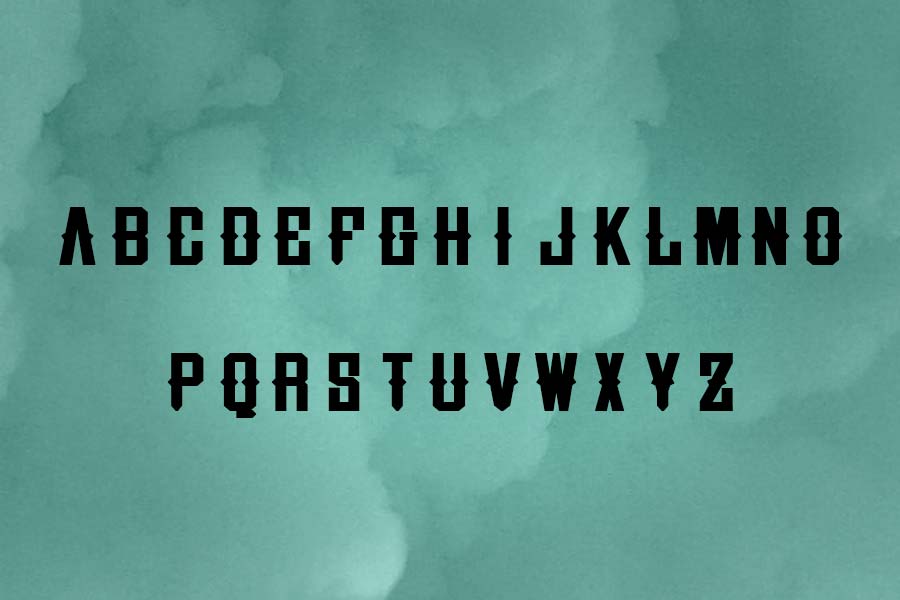
Siguiendo la marcha con Monday font, os dejamos una nueva fuente tipográfica para descarga totalmente gratuita. El turno de hoy es para Rude, una fuente san serif con un pequeño remate bastante vistoso. Es la primera creación tipográfica del diseñador Dre 1